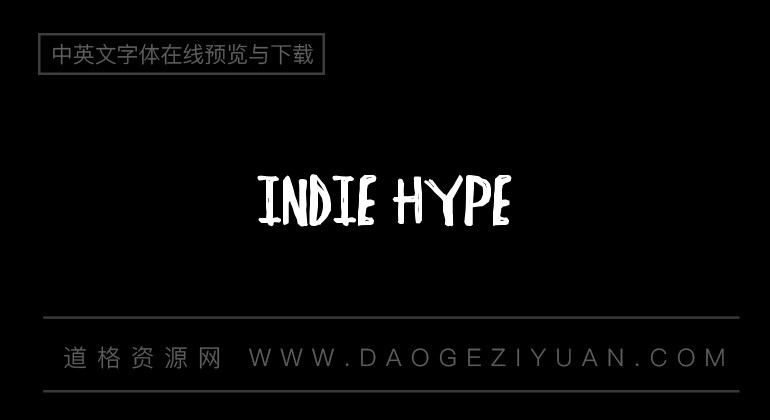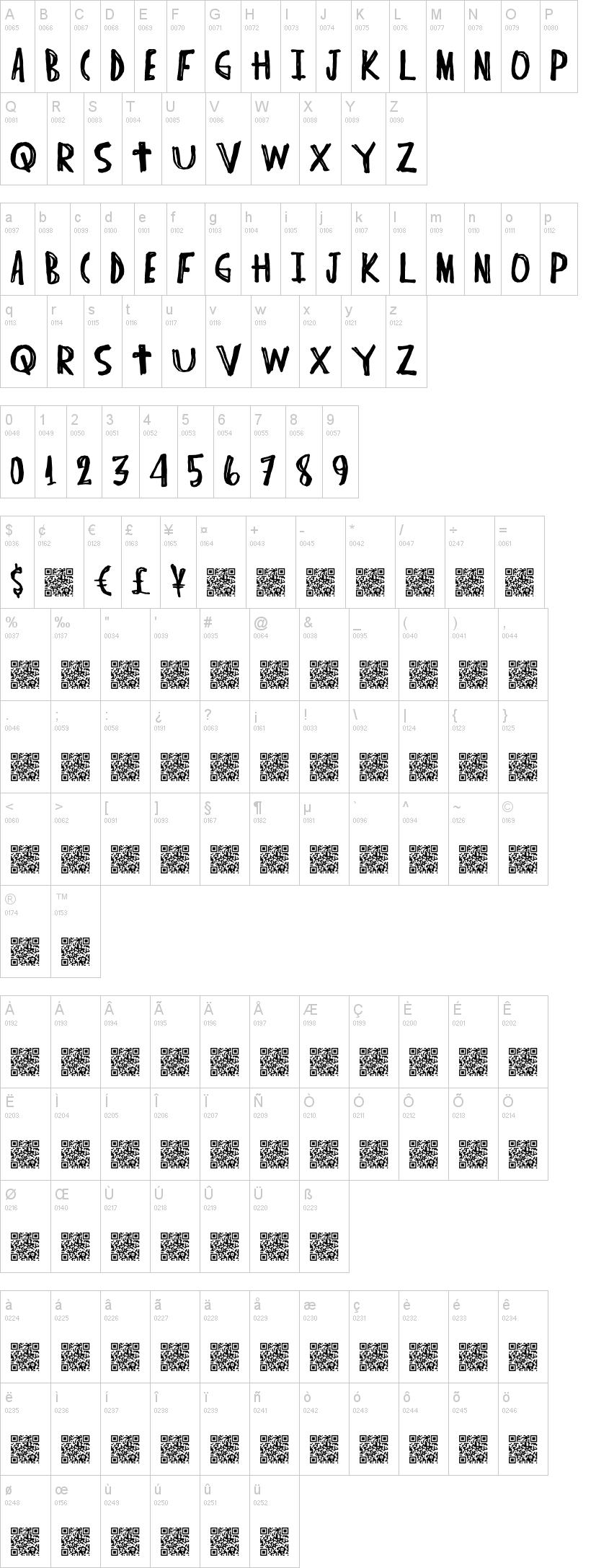
Indie Hype 是一种类似于手写字体的字体样式,其字母形状和笔画都非常有特色。这种字体常常被用于设计海报、书籍封面、音乐专辑封面等艺术设计领域。Indie Hype 字体的特点是具有很强的视觉吸引力和个性化,同时也很好地表达了非正式和独立的创意氛围。由于其非常适合用于创意设计,因此这种字体在网络上也很受欢迎,被广泛地应用于各种社交媒体平台上,例如 Instagram、 Tumblr 等。内容介绍
Indie Hype是一款非常不错的手写艺术字体,具有很好的视觉感,适合于文化类的宣传设计、商业类品牌的广告和产品包装设计以及个性化文字排版等较多场景。